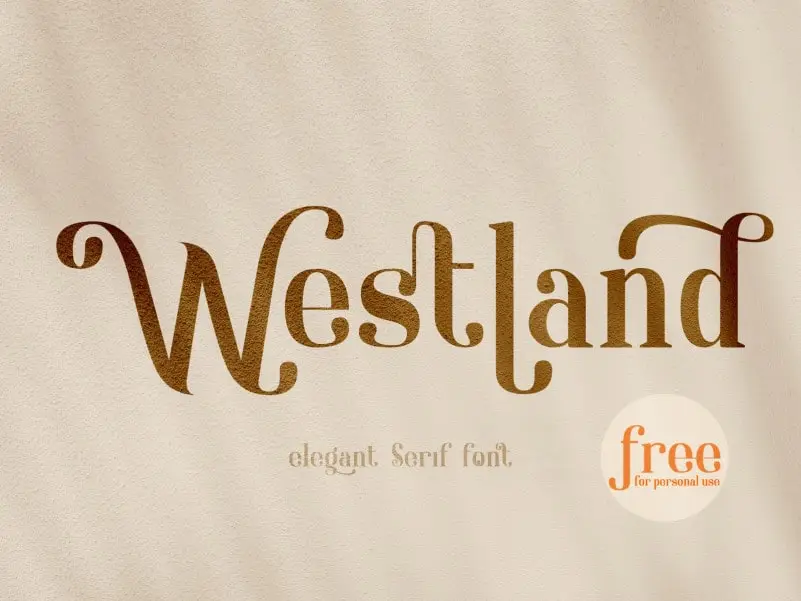
Westland Serif Font – Download Grátis
Westland Serif é uma elegante tipografia serif que surpreende com sua singularidade. Esta fonte fácilmente se encaixa em uma ampla gama de projetos, tornando-a uma escolha perfeita para designers buscando criar experiências criativas ainda mais atraentes e únicas. Com o PUA encoding que lhe permite acessar todas as suas caligrafias e swashes com facilidade, este é um recurso gráfico que merece estar em sua biblioteca de fontes. Seja você designer ou artista digital, Westland Serif oferece a oportunidade de dar mais destaque aos seus trabalhos, tornando-os ainda mais imprimíveis e memoráveis.